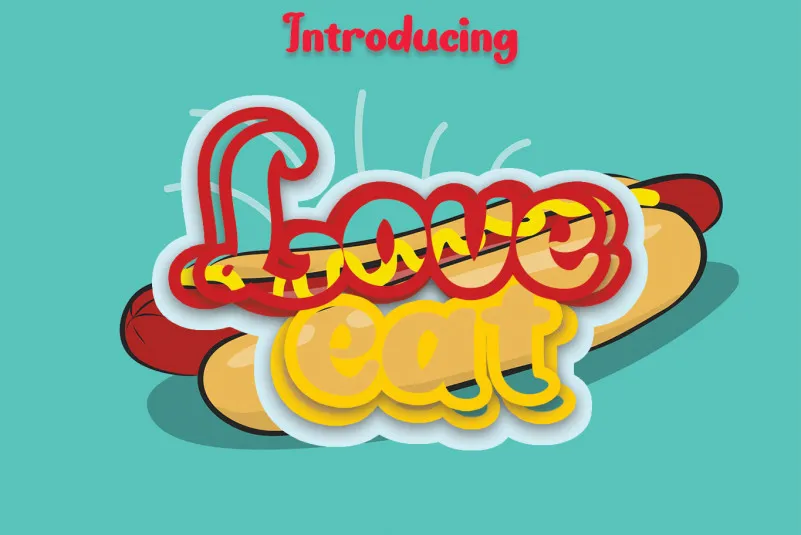
Love Eat Font – Download Grátis
Esta é uma fonte cíntica bela e agressiva que exala elegância e classe. Foi especialmente desenvolvida para quem precisa de uma aparência atraente e renovadora em suas criações. Perfeito para adicionar um toque único e moderno ao seu design, a Love Eat Font é perfeita para designers buscando trazer sofisticação ao seu trabalho. Esta fonte é ideal para criar elementos visuais que transmitem elegância e beleza, tornando-a uma escolha ótima para qualquer projeto de layout ou criação gráfica. Composta por linhas fortes e traços bem definidos, essa fonte cíntica traz um toque único à sua obra, atraindo os olhos para seu design.